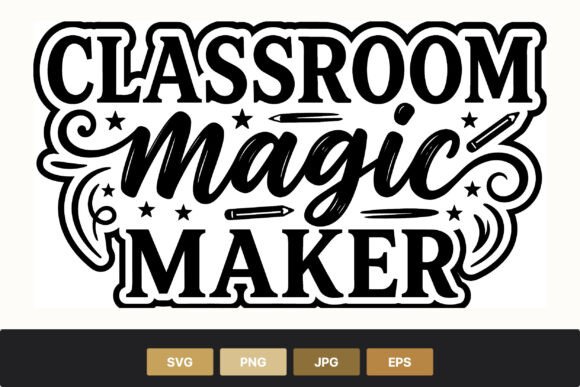
Classroom Magic Maker Script Serif
Jika anda sedang mencari aset berkualiti tinggi seperti Classroom Magic Maker Script Serif, pakej premium ini merupakan pilihan yang hebat untuk projek kreatif anda.
Sama ada anda mencipta produk POD (Print on Demand), jemputan perkahwinan atau grafik media sosial, Classroom Magic Maker Script Serif amat bersesuaian.